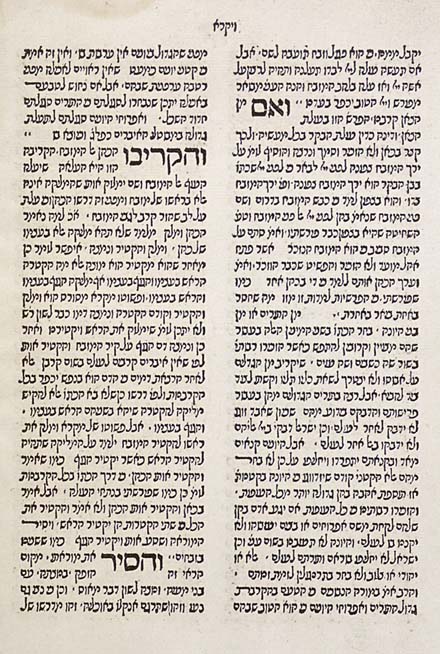
Eliezer Toledano (séc XV e XVI)Escolástico de Toledo. Prototipógrafo judeu que imprimiu a partir de 1489 em Lisboa. Conhecemos seis incunábulos de sua autoria.Em Portugal, Eliezer Toledano imprimiu em 16 de Julho de 1489 Hiddushe ha-Torah (as Novas da Lei ou Comentário ao Pentateuco), de Moses ben Nahman (1194 - c.1270), um rabi catalão, também conhecido pelo nome latino Namánides.
... E imprimiu o Comentário à Ordem das Orações, de David Abudarham. (Notícia sobre um leilão) Em 1490 imprimiu em Lisboa o Livro de Orações e Caminhos do Mundo, de Josué Levi, o Livro do temor, de Jonah Gerondi, os Segredos da Penitência, de Ionm Tovb, todos formando um volume. Em 1491 deu à estampa o Pentateuco, na versão de Onkelos e comentário de Rashi e, em 1492, os Provérbios de Salomão. Neste ano imprime também Isaías e Jeremías, comentário de David Kimji e as Leis da Matança de Moisés ben Maimon. Antes de se fixar em Lisboa, Eliezer Toledano viveu em Toledo e talvez em Hijar (o material da sua oficina tipográfica era proveniente de Hijar). Alguns historiadores julgam que o físico Elieser ben Alantansi que foi impressor em Hijar, é a mesma pessoa que ET, o que explicaria o facto de no último livro impresso no prelo de Hijar, o Pentateuco de 1490, já não figurar o nome de Elieser ben Alantansi e de a casa ter fechado após aquela data. Outros autores defendem que Elieser Toledano não foi impressor mas sim proprietário de tipografia e editor. Na sua oficina gráfica trabalharam Judah Gedaliah, Zaqueu, seu filho, e Moisés, filho de Semtob. Como revisor de algumas obras impressas na tipografia de Eliezer aparece o nome de Joseph Calphon. Elieser Toledano teve que abandonar a actividade tipográfica em 1492, quando os judeus foram expulsos de Espanha. É possível que tenha partido para Fez, e aí tenha prosseguido a sua actividade de impressor ou editor. Judah Gedaliah foi um tipógrafo judeu nascido em Lisboa; trabalhou na oficina de Eliezer Toledano até à expulsão dos judeus de Portugal em 1497. Depois foi para Salónica, onde fundou a primeira tipografia na cidade com o material que tinha trazido de Lisboa. Depois da sua morte, a sua oficina foi continuada pelos filhos. |